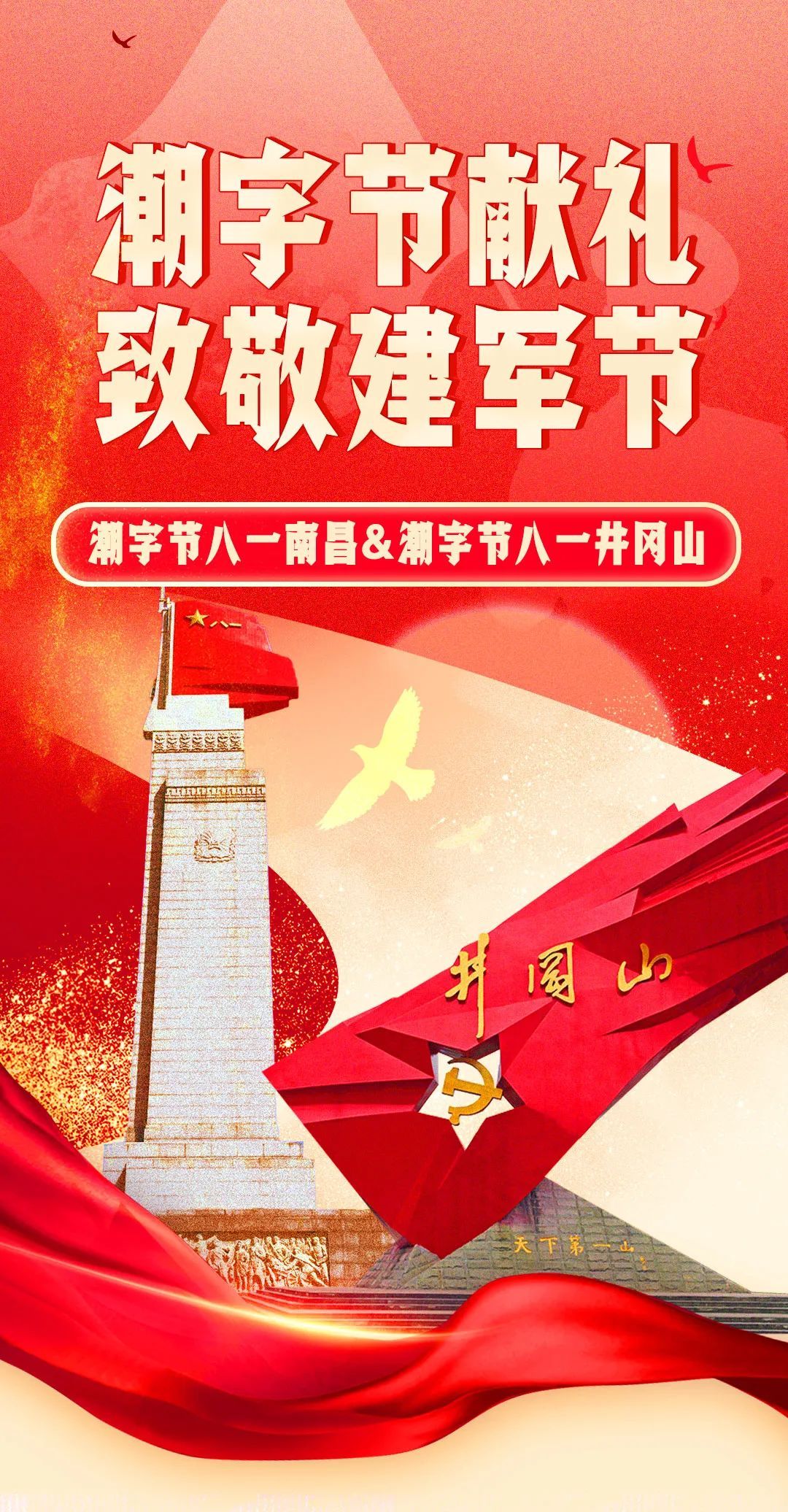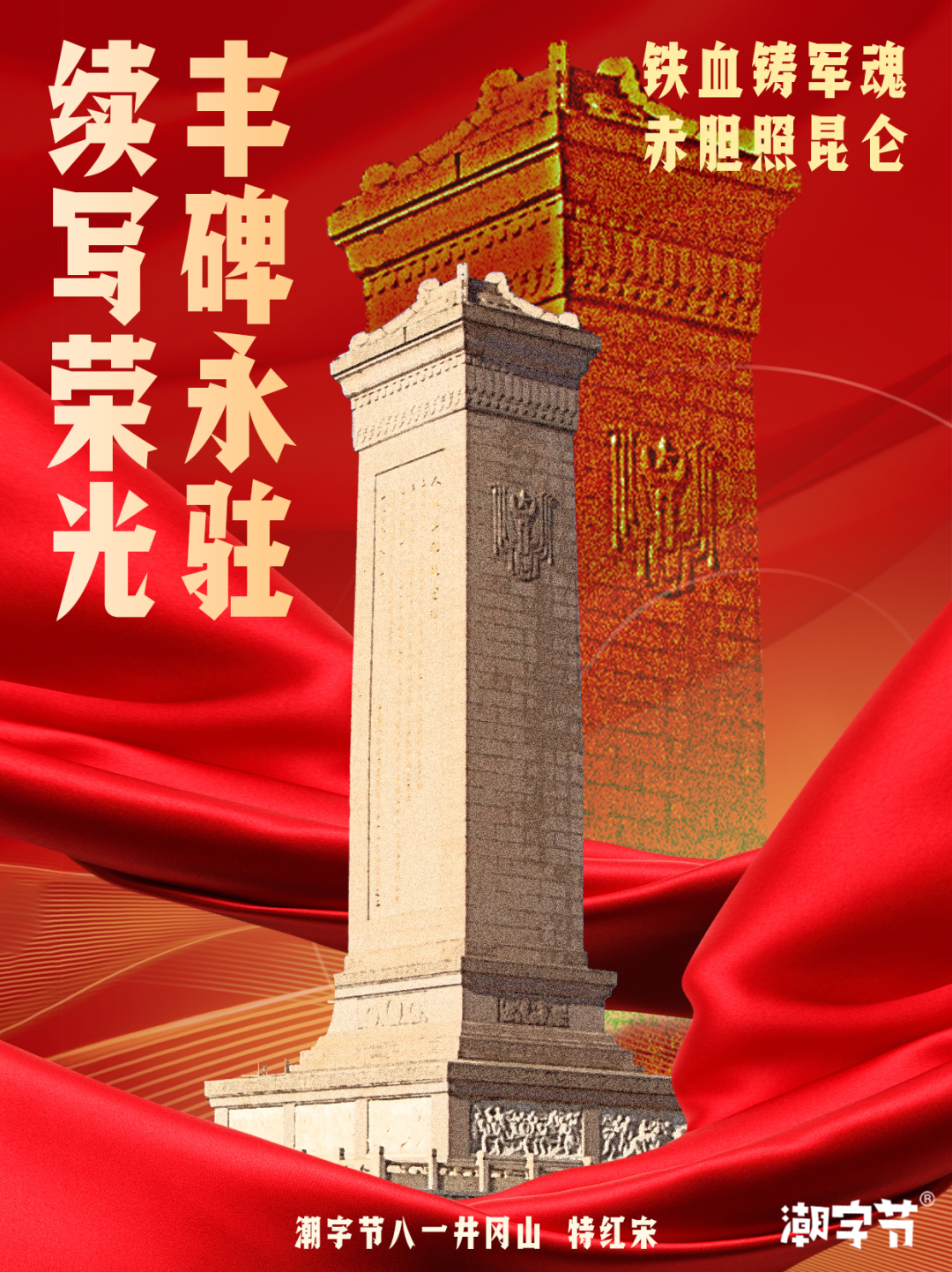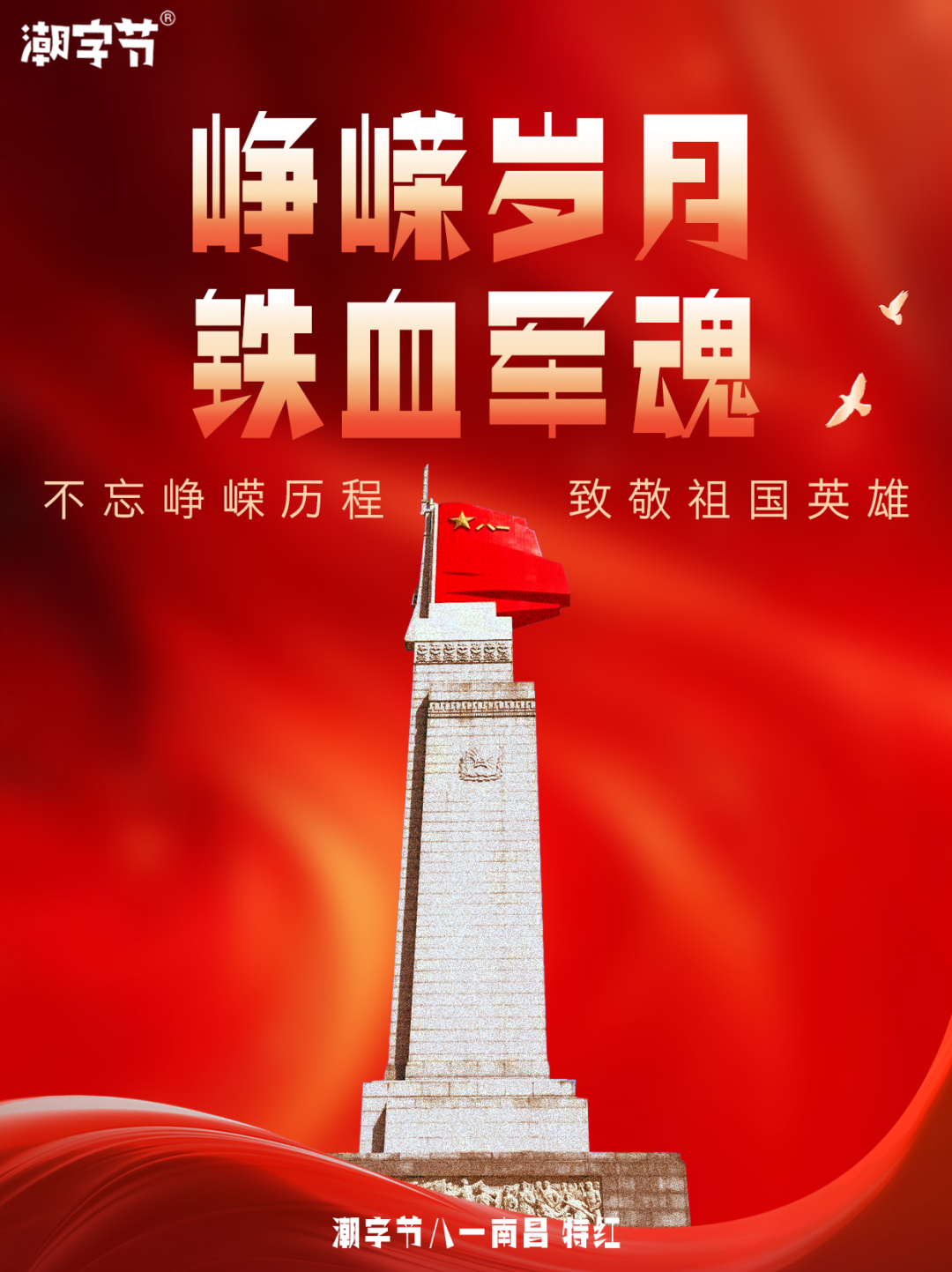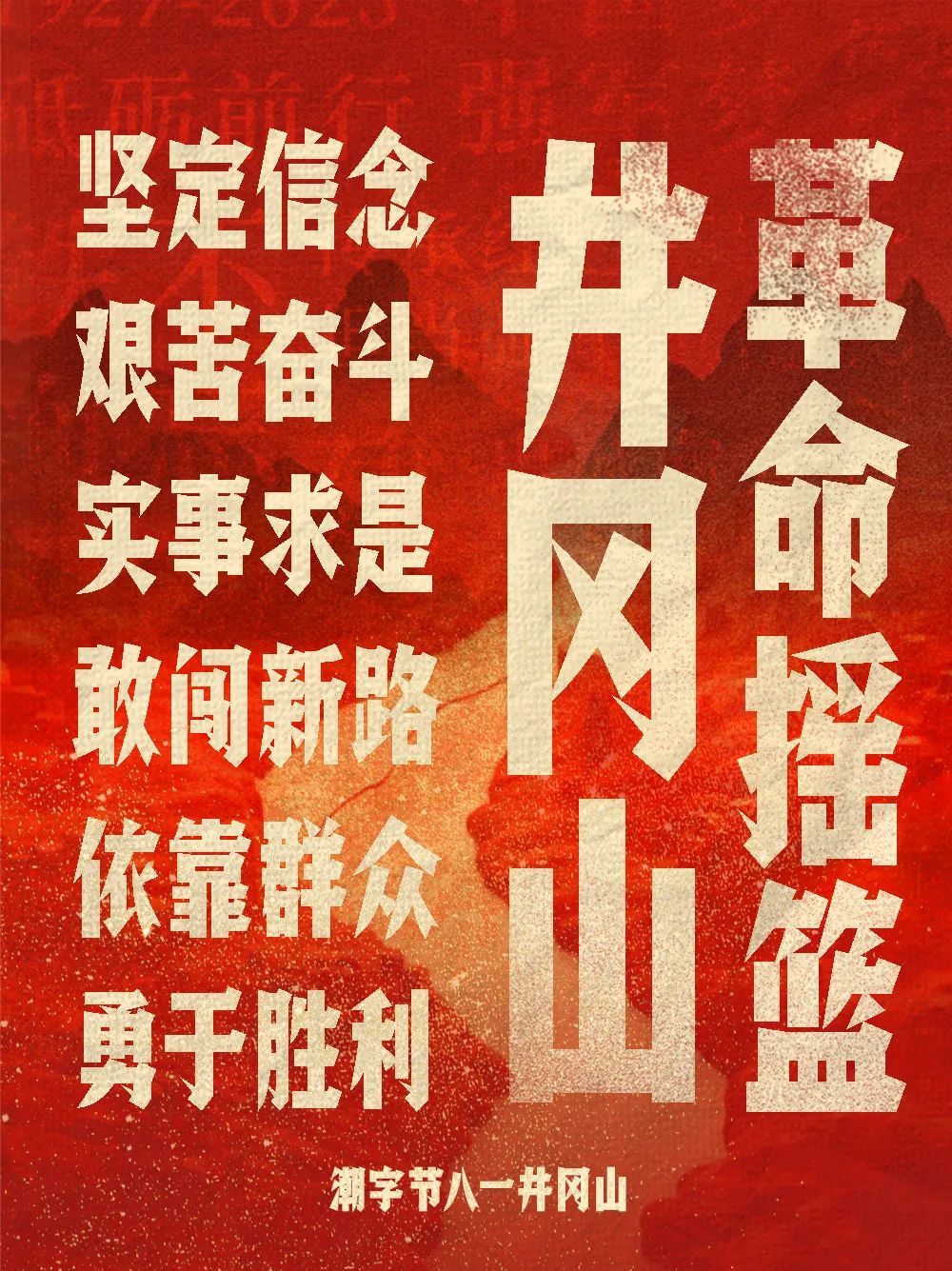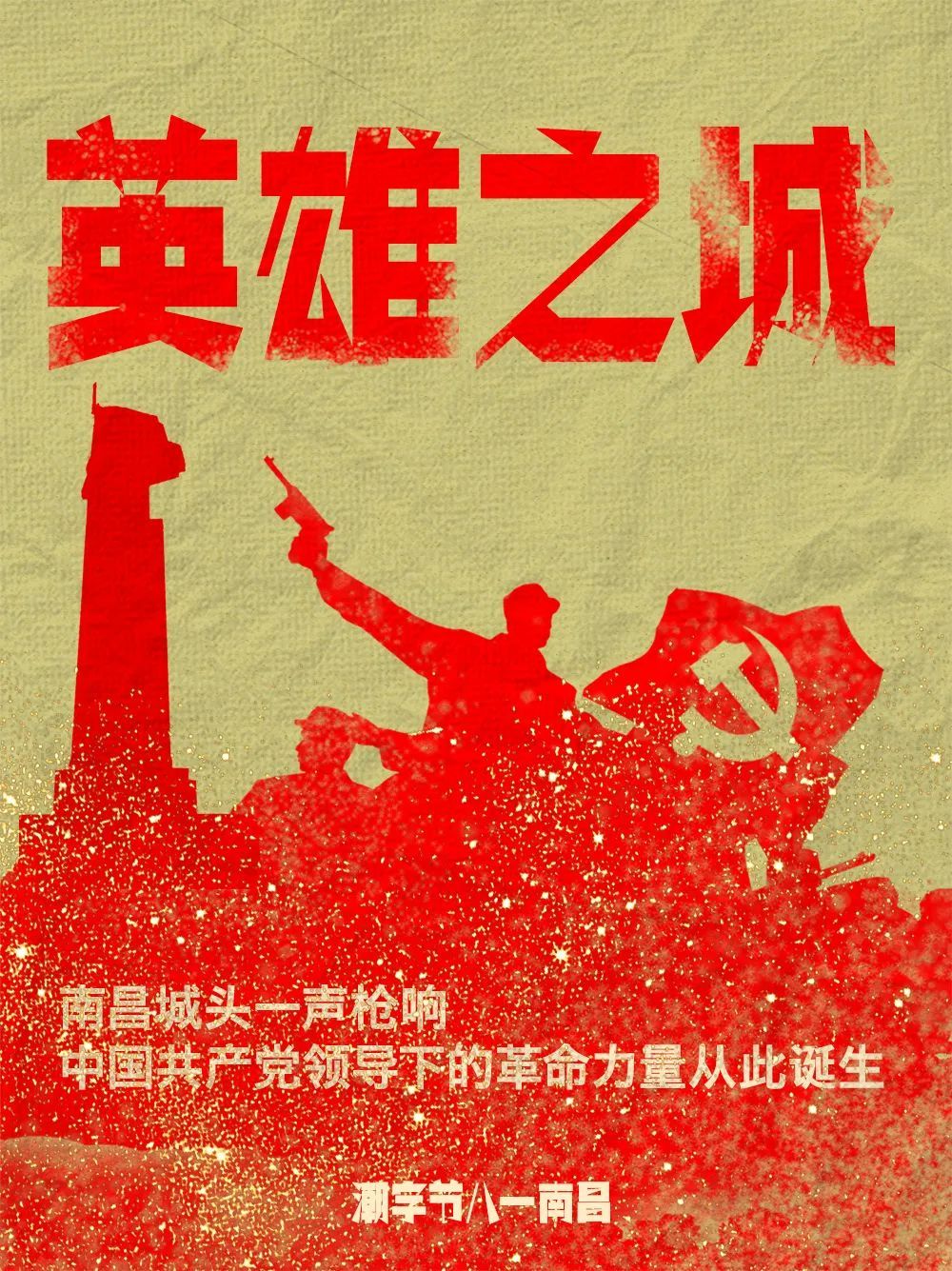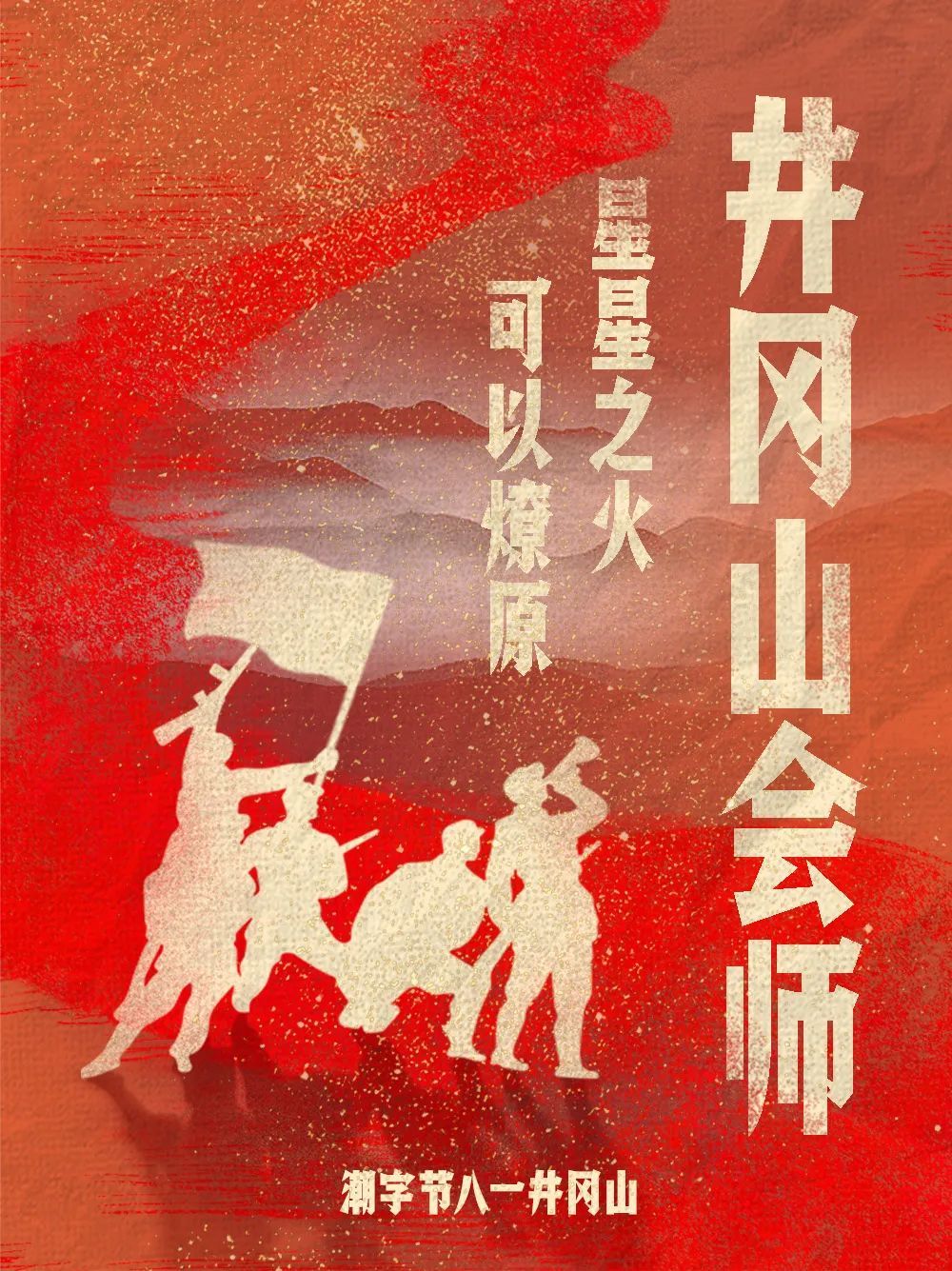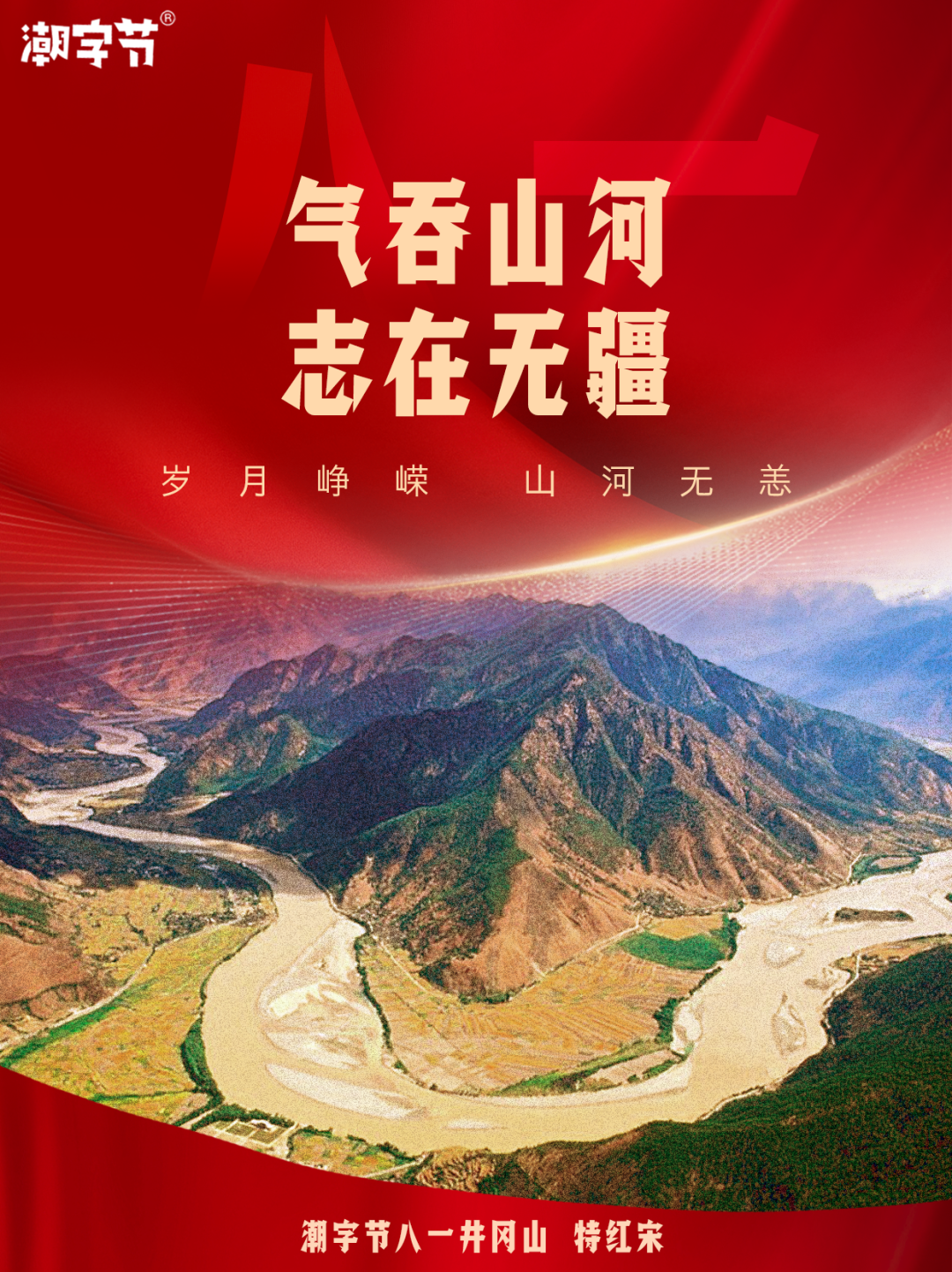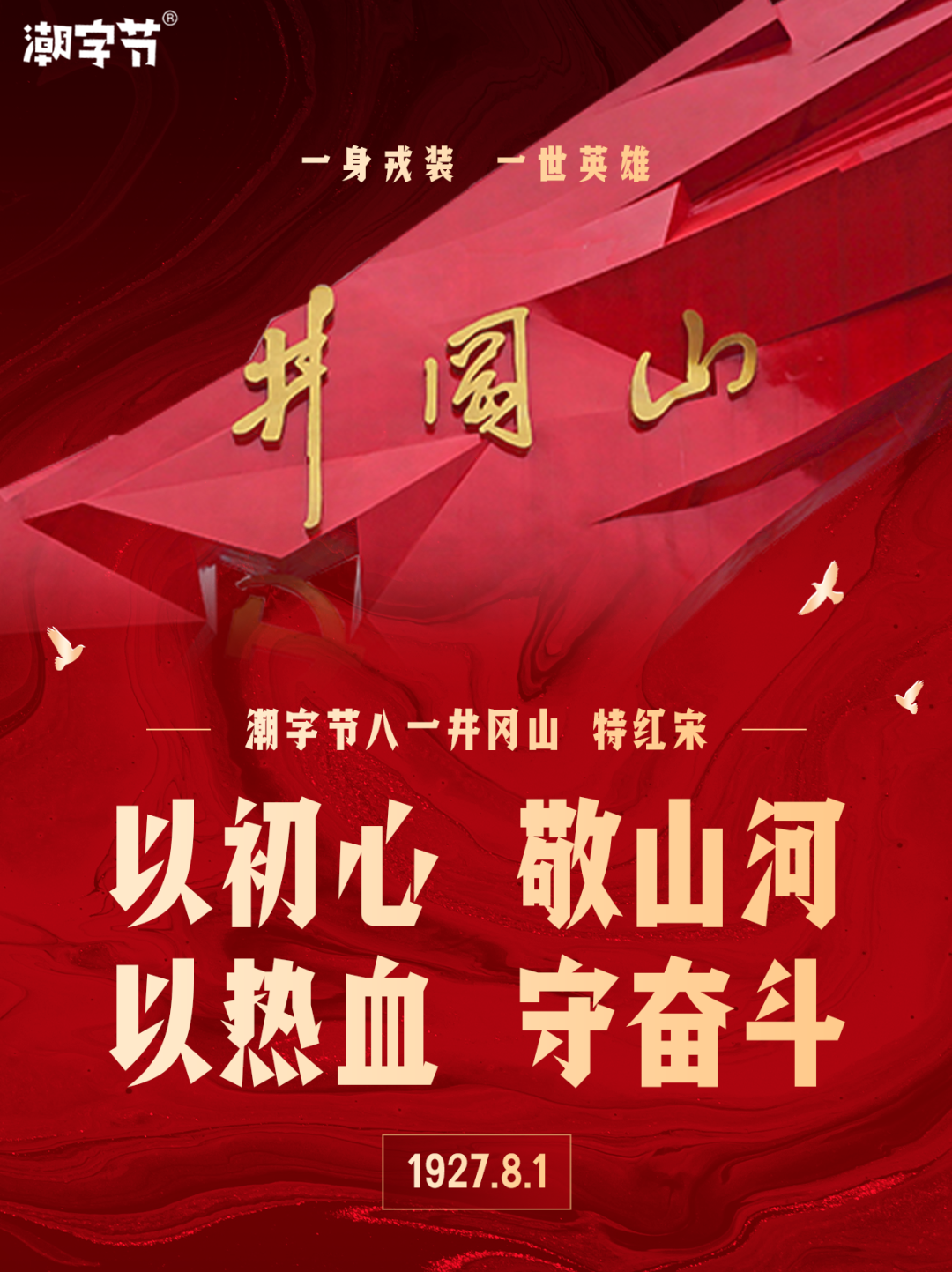
八一建军节,是中国人民解放军建军纪念日,它见证了历史,见证着中国军人的坚韧与忠诚。战争年代,他们用坚定的信念、无畏的精神,冲锋陷阵、不怕牺牲;和平岁月,他们练兵备战,抢险救灾,当祖国和人民需要时挺身而出、无私奉献。
潮字节特别献礼,推出2款红色字体——潮字节八一南昌&潮字节八一井冈山,作为建军节公益定向免费商用字体,旨在铭记历史,传承与弘扬红色精神,向那些为国家安全、人民幸福默默奉献的军人们致以崇高的敬意!
1927年的南昌起义,打响了武装反抗国民党反动派的第一枪,标志着中国共产党独立领导武装斗争和创建革命军队的开始。
1927年10月,毛泽东率领工农革命军上了井冈山,创建了以宁冈为中心的井冈山革命根据地。
1928年4月28日井冈山胜利会师是中国人民解放军建军史上的重要历史事件。对巩固扩大全国第一个农村革命根据地,推动全国革命事业的发展,具有深远的意义,星星之火,从此处开始燎原。
1933年7月11日,中华苏维埃共和国临时中央政府根据中央革命军事委员会6月30日的建议,决定8月1日为中国工农红军成立纪念日。中华人民共和国成立后,此纪念日改称为中国人民解放军建军节。
建军节不仅仅是一个纪念日,它更是对革命先烈的缅怀,对红色精神的传承。潮字节八一南昌&潮字节八一井冈山,作为红色字体,一笔一画,都凝聚了对历史的敬仰和对红色精神的深刻理解。
潮字节八一南昌、八一井冈山两款字体在设计过程中,将南昌起义的英勇与井冈山精神的坚韧不拔融入其中,刻画着军人的信念与无畏,让人们铭记那段波澜壮阔的历史,感受到历史责任感和使命感。
潮字节八一井冈山,灵感来源于中国革命摇篮井冈山和星火燎原的革命精神,是一款风格极其强烈的宋黑标题字,字如将士威严伫立,气势非凡,让人心生敬畏。
字面高挑,中宫宽博,纯直线构成的骨骼结构十分硬派,留白均匀,整体端庄从容。
笔画几乎由直线构成,横竖笔画作为基石,粗壮如柱,样式简洁现代,横笔的收尾与折笔的肩膀向斜上折起,借鉴了宋体的顿笔装饰角与三角肩的特征,既继承传统,又突破革新,钩捺犀利如刀,点提撇画犹如尖锥利剑,形象自有威严。
潮字节八一南昌体是一款个性非常强烈、有着独特视觉体验的创意黑体。字形饱满,在粗壮厚实的笔画中穿插了别具一格的几何三角形与细笔画,带给人强烈的视觉冲击,如同被打破的僵局和即将发生的激战一般,展示出敢于抗争、不畏艰难的中国军人精神。
潮字节八一南昌与潮字节八一井冈山体不仅具有深厚的文化内涵,还具有很强的实用性。在八一建军节期间,可以广泛应用于各类宣传海报、节日标语等场景。
建军节不仅仅是一个纪念日,更是对军人精神的传承和弘扬。我们希望通过两款字体铭记历史,铭记那些为国家、为人民付出青春和热血的军人们,传达不忘初心,牢记使命,为实现中华民族伟大复兴的中国梦而努力的奋斗精神。